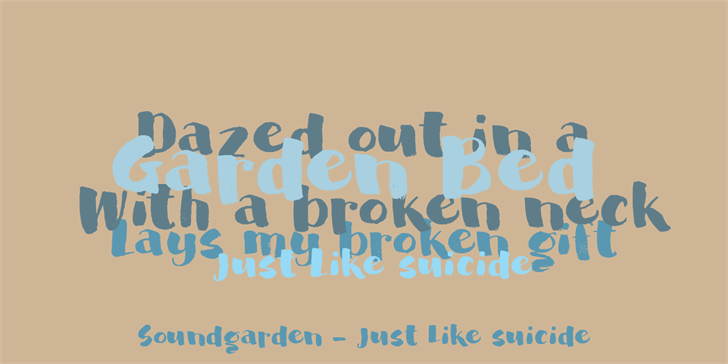
A fonte DK Garden Bed é uma elegante futeve brush font criada pelo designer Hamilton. Suavemente elaborada, ela captura a essência das plantas e do jardim, oferecendo um visual único que combina com o estilo minimalista moderno dos recursos gráficos. Esta fonte vem em versão gratuita apenas para uso pessoal. Se você planeja usá-la comercialmente, é melhor adquirir a versão completa disponível em seu site oficial, onde encontrarás também tudo aquilo que a make-up do arquivo zip: kerning, direitos de embedding e todos os góticos extras disponíveis em hanodedfonts.com. Sem dúvida, DK Garden Bed fará uma excelente escolha para aqueles que desejam personalizar gráficos com um toque natural e vivo de natureza.